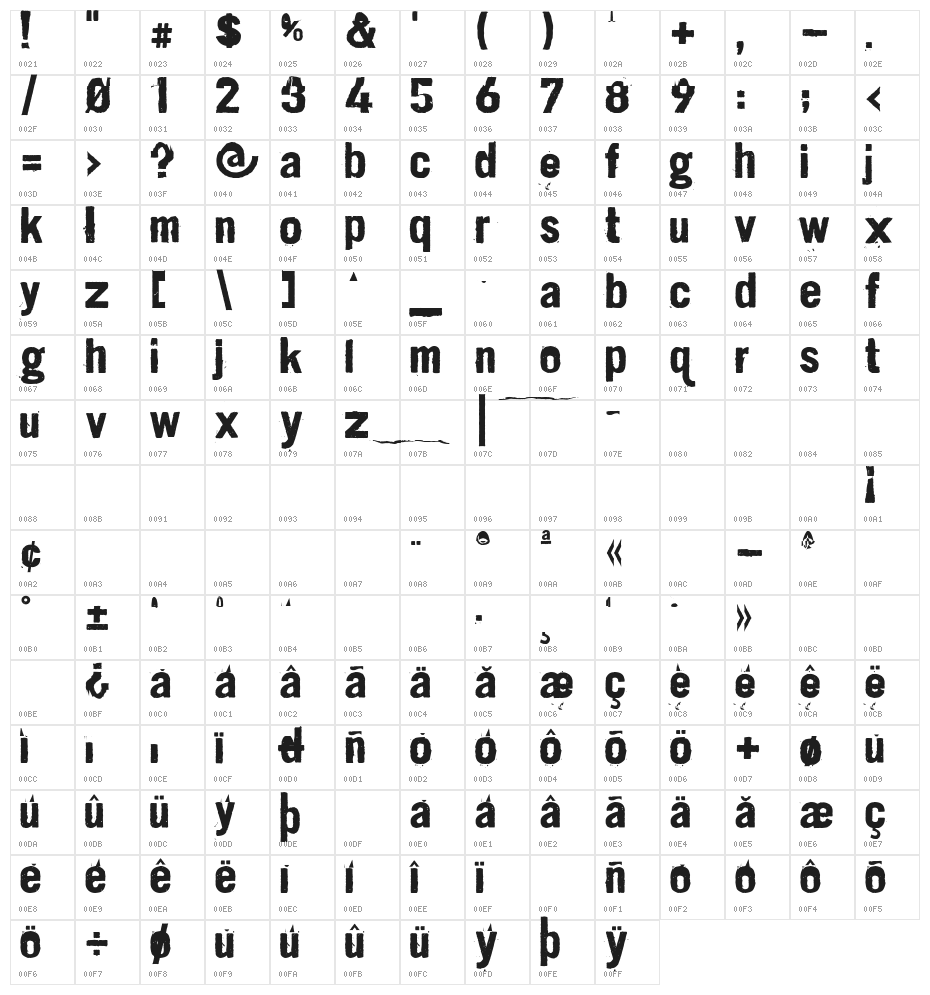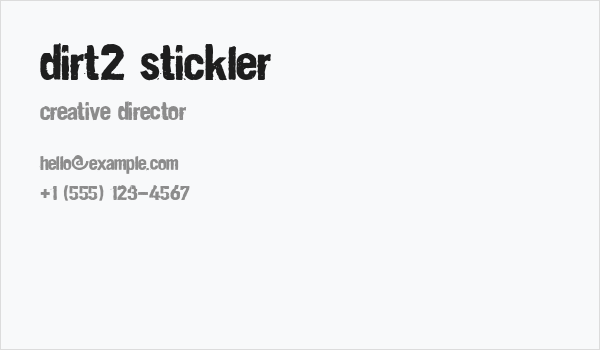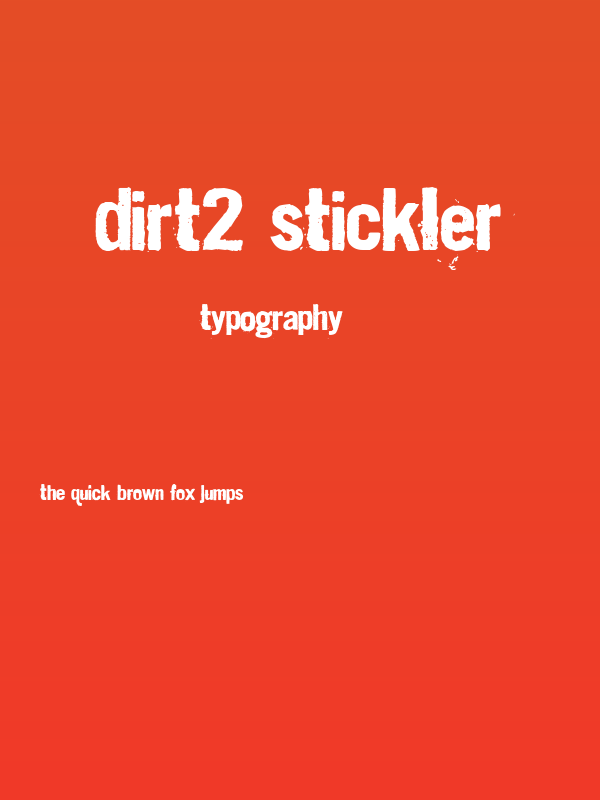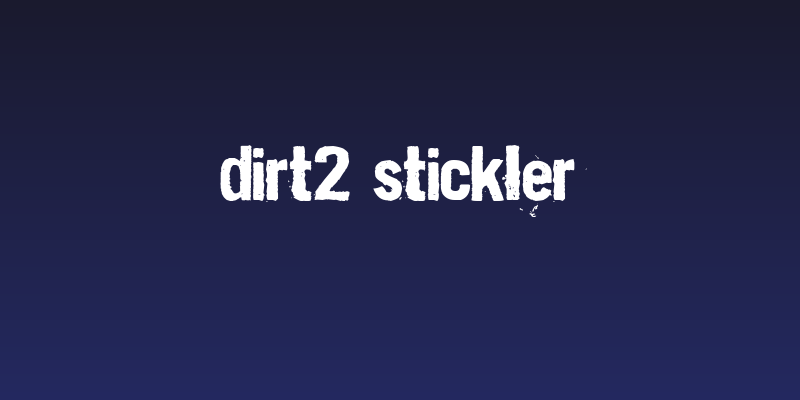
Dirt2 Stickler Font
✎ Distorted Eroded
| 分类 | Distorted Eroded |
| 宽度 | Condensed |
| 推荐项目 | Ideal for posters, album covers, streetwear branding, and any design needing a gritty, urban vibe. |